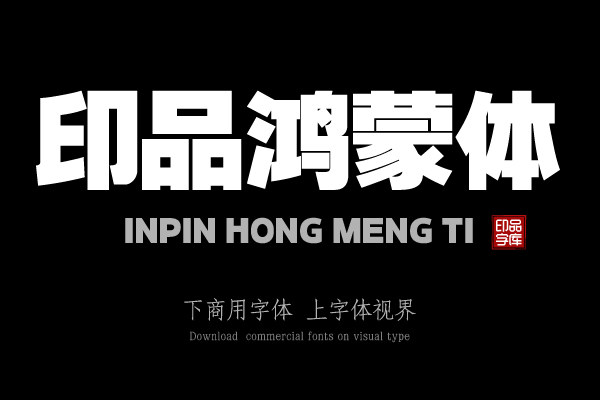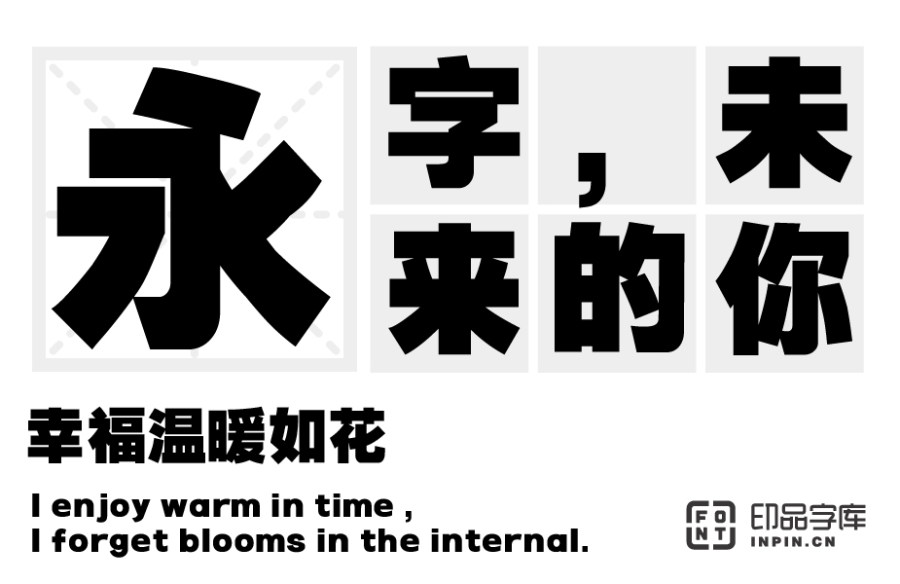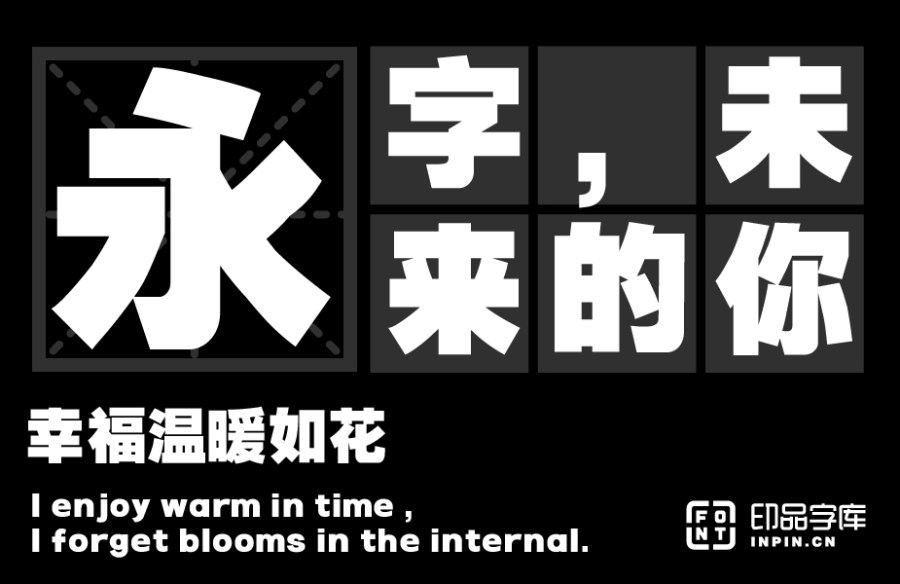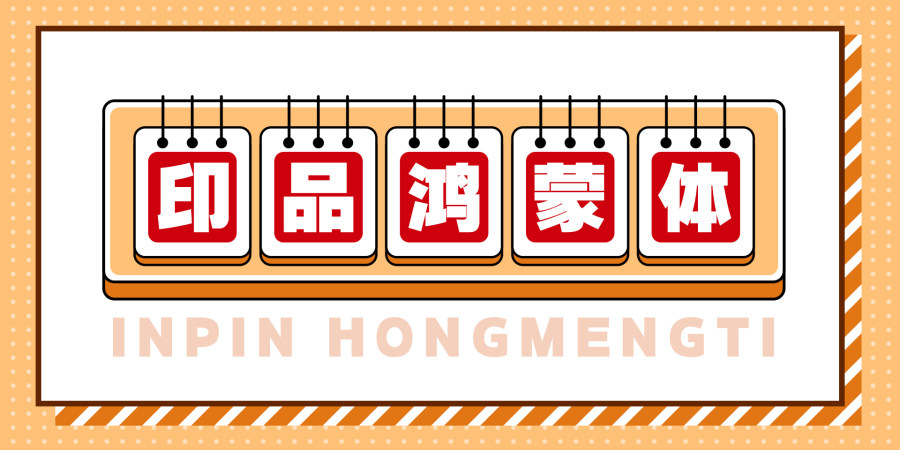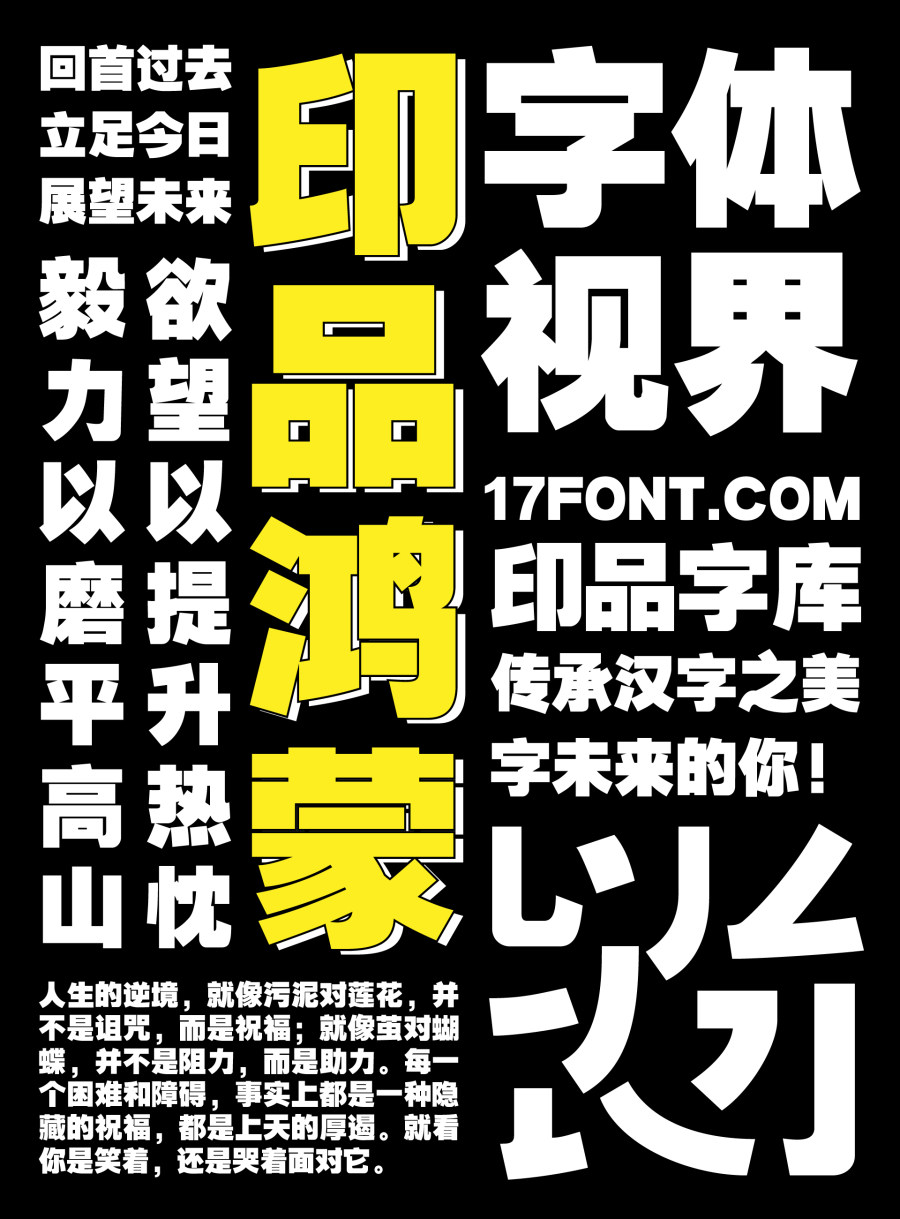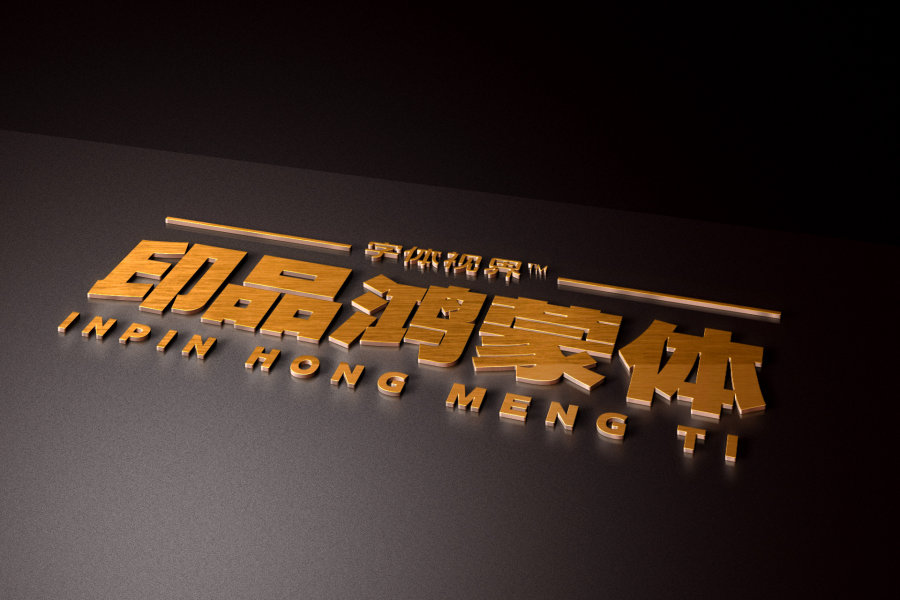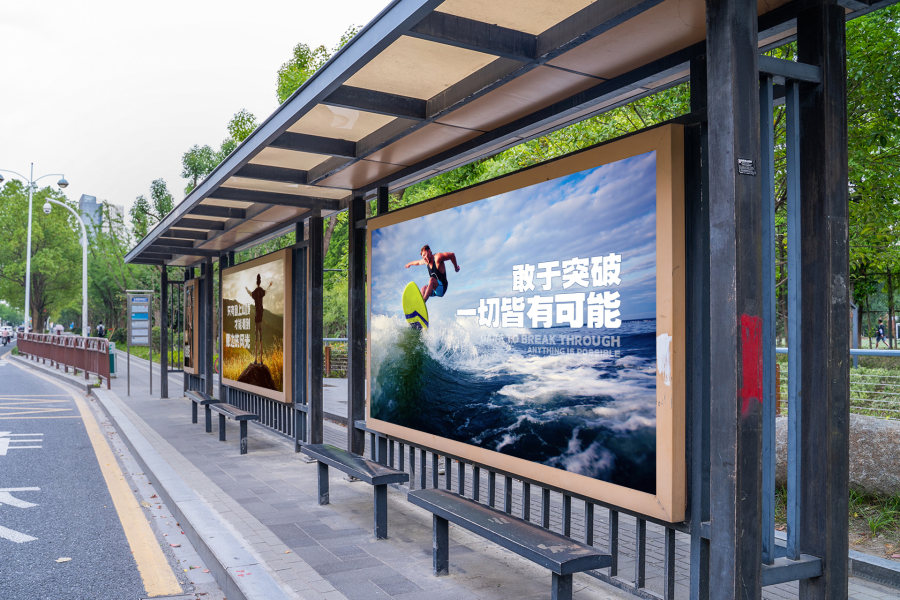
印品鸿蒙体 超粗黑版
印品鸿蒙体结构严谨端庄,字形饱满,字体间距布局均匀讲究 ,整体美观又大方,整体风格刚劲有力而又不失俊儒之风;笔画之中蕴含古朴沉厚端凝之势,在主标题上有很大的应用......
• 印品鸿蒙体结构严谨端庄,典型黑体字型。字形饱满,字体间距布局均匀讲究 ,整体美观又大方;横竖笔画粗细保持一致,整齐划一,凸显出精简精干的特点,粗壮有力的笔划赋予其力量感,整体风格刚劲有力而又不失俊儒之风;笔画之中蕴含古朴沉厚端凝之势,在主标题上有很大的应用空间。笔画粗壮,适合与宋体混排,夹在正文中间用来排重点句、重点词组效果很好。